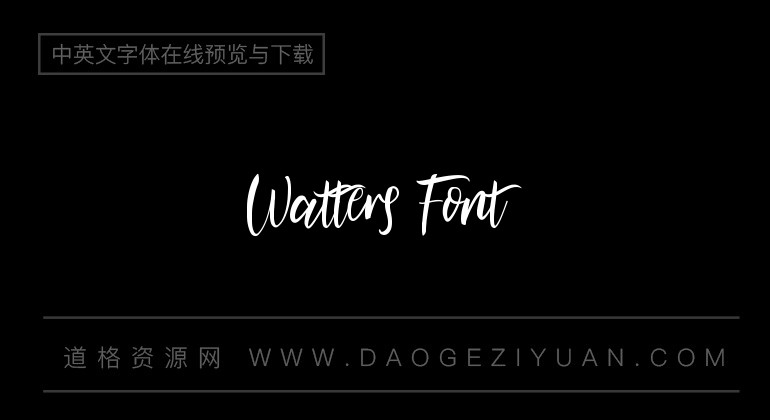
Watters Font 是一款漂亮的手写风格字体,由美国的设计师 Tom Chalky 创作。这款字体的风格非常适合用于卡片、海报、标语、广告和几乎任何需要手写风格的设计项目中。 Watters Font 的设计风格非常自然,仿佛是由一个人用钢笔、墨水和纸张手写而成。它包含大写字母、小写字母、数字和标点符号,具有非常好的可读性和美观度。 Watters Font 有两种版本:普通版和斜体版。这两种版本都支持多种语言,包括英语、西班牙语、德语、法语、意大利语等等。此外,它还包含了很多特殊字符和花式字母,使得您的设计项目更加独特。内容介绍
Watters Font是一款非常不错的手写艺术字体,具有很好的视觉感,适合于文化类的宣传设计、商业类品牌的广告和产品包装设计以及个性化文字排版等较多场景。